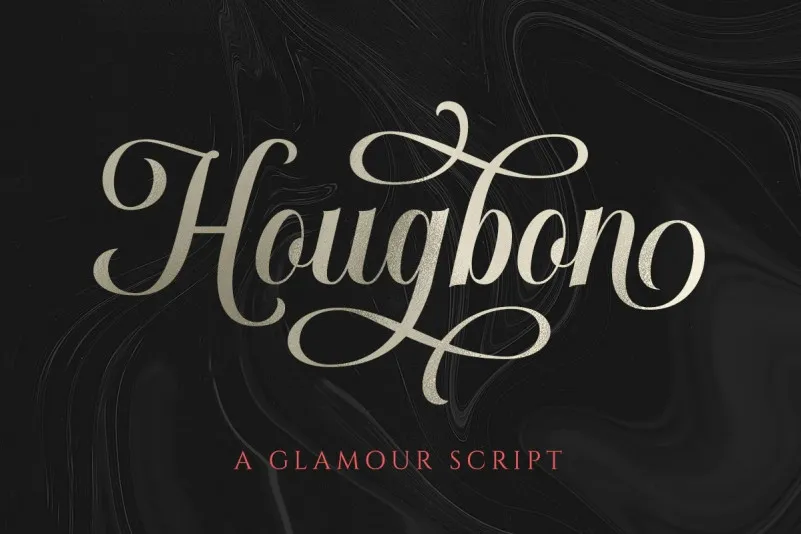
Esta fonte ‘Hougbon Font’ é perfeitamente adaptada para qualquer tipo de projeto que exija uma aparência elegante e casual no mesmo instante. Foi projetada para designers que valorizam um estilo moderno, combinando liberdade criativa com um toque de precisão cuidadosa. Cada caractere pode ser personalizado em até oito setos estilísticos separadamente, garantindo uma vasta gama de opções para personalizar sua marca ou conteúdo. O Hougbon Font foi meticulosamente elaborado para abordar múltiplas necessidades práticas e criativas. Suaviza formalidades como cartões de convite, rótulos, logotipos, revistas, livros, cartas de aniversário ou casamentos, embalagens, moda, maquiagem, material escolar, novelos e qualquer tipo de propósito publicitário. Além disso, a fonte oferece suporte para números, símbolos e sinais gráficos. Um detalhe que torna este font especialmente útil é sua PUA (Private Use Area) encoded, que permite utilização em outras aplicações design sem necessidade de recursos de OpenType. Esta característica se torna particularmente valiosa para designers digitais em fluxo constante que precisam usar essa fonte sem preocupações adicionais.